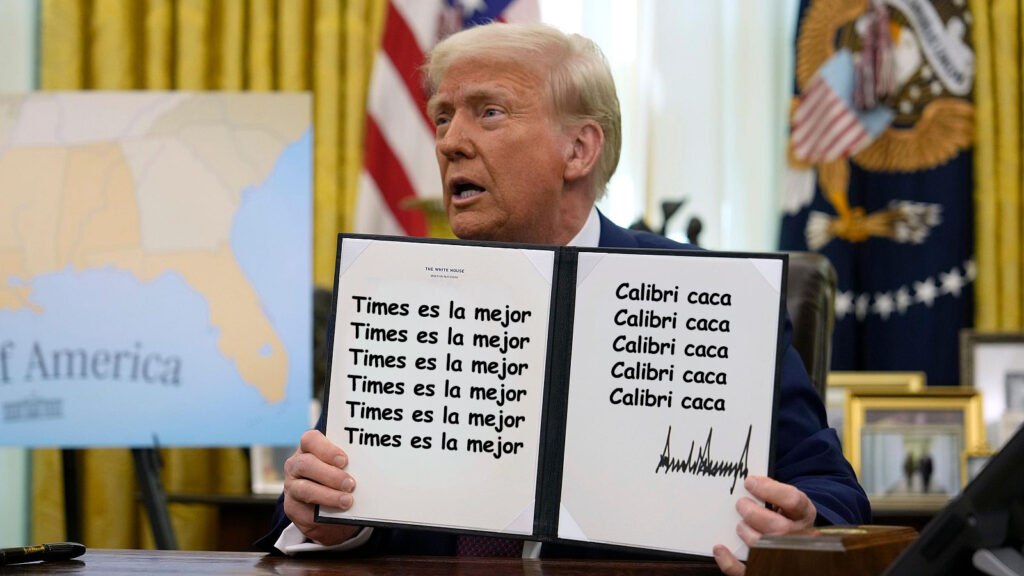
¿Puede una tipografía tener afinidad política? El diseño como nuevo campo de batalla ideológico
Durante décadas, la tipografía ha sido uno de los grandes elementos invisibles del poder. Siempre presente en leyes, documentos oficiales y comunicación institucional, rara vez ha sido cuestionada. El reciente cambio de Calibri a Times New Roman ordenado por la administración Trump en el Departamento de Estados Unidos ha roto ese silencio y ha abierto un debate inesperado: ¿puede una tipografía tener afinidad política o estamos proyectando ideología sobre una herramienta técnica?
La relación entre tipografía y poder no es nueva. En los casos más extremos, las letras han funcionado como símbolos ideológicos explícitos. Las tipografías góticas utilizadas por el régimen nazi en los primeros años del Tercer Reich condensaban una idea de tradición nacional frente a la modernidad internacional. Aunque su uso no fue constante ni obligatorio, la asociación quedó fijada en la memoria colectiva.